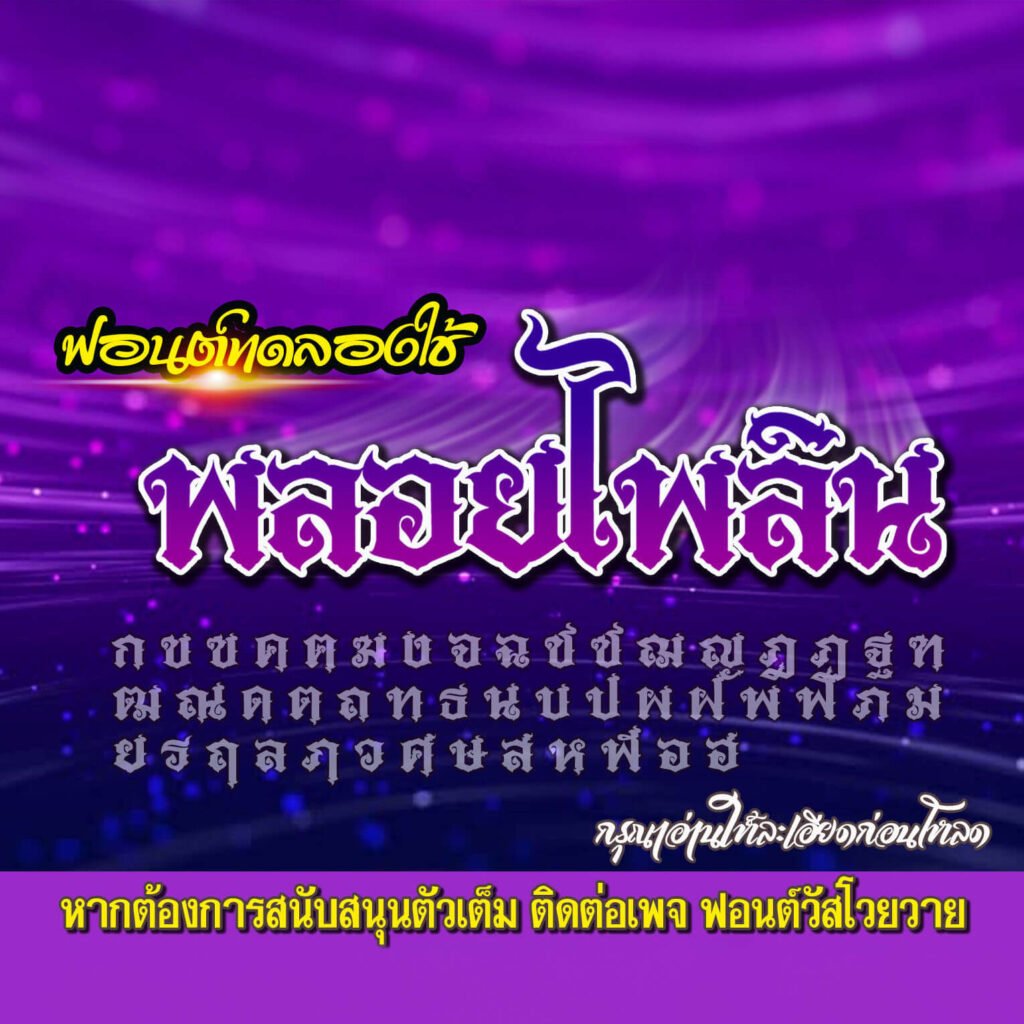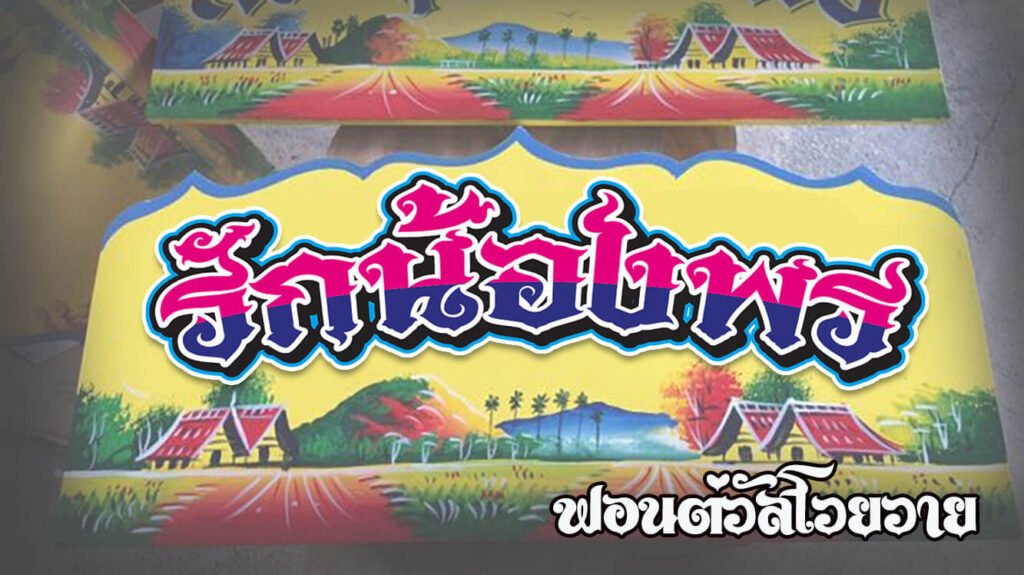
พลอยไพลิน (was@ploypilin)
ฟอนต์พลอยไพลิน มีต้นแบบมาจากการแกะโฟมของอาจารย์ท่านหนึ่ง ซึ่งผมได้เห็น ร.เรือ เพียงตัวเดียว
ก็รู้สึกสนใจ และชื่นชอบในความงดงามของตัวอักษร จึงทำให้ผมประดิษฐ์ตัวอื่นๆ ขึ้นจากจินตนาการของผมเอง
ซึ่งก็เป็นการดี ที่จะเป็นตัวของตัวเองมากกว่าที่จะมีแบบอยู่แล้ว ซึ่งเราก๊อปมาล้วนๆ
การทำฟอนต์นี้ใช้เวลาพอสมควร ซึ่งมันก็ไม่ลงตัวง่ายๆ เปลี่ยนไปมาอยู่หลายตัว จนมาถึงตัวที่ผมคิดว่ามันน่าจะเหมาะสมที่สุด (สำหรับผม) สำหรับท่านอื่นคิดเห็นอย่างไร ลองทักทายมาพูดคุยเสนอแนะกันครับ